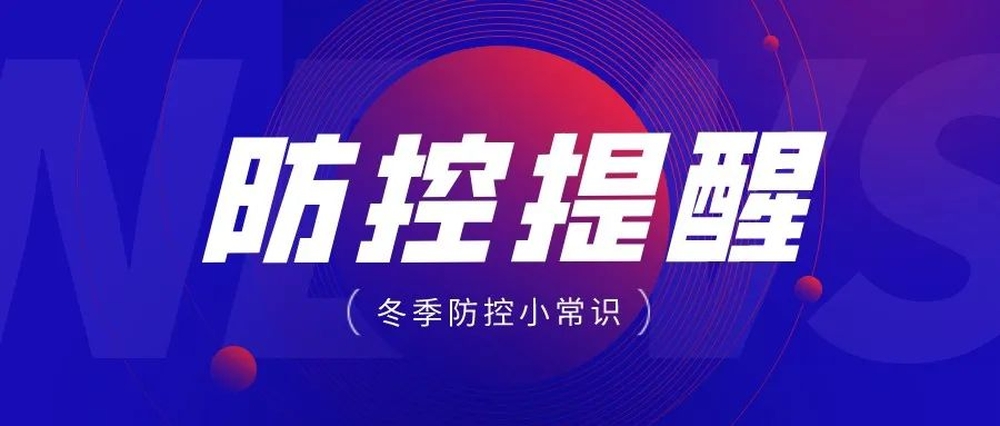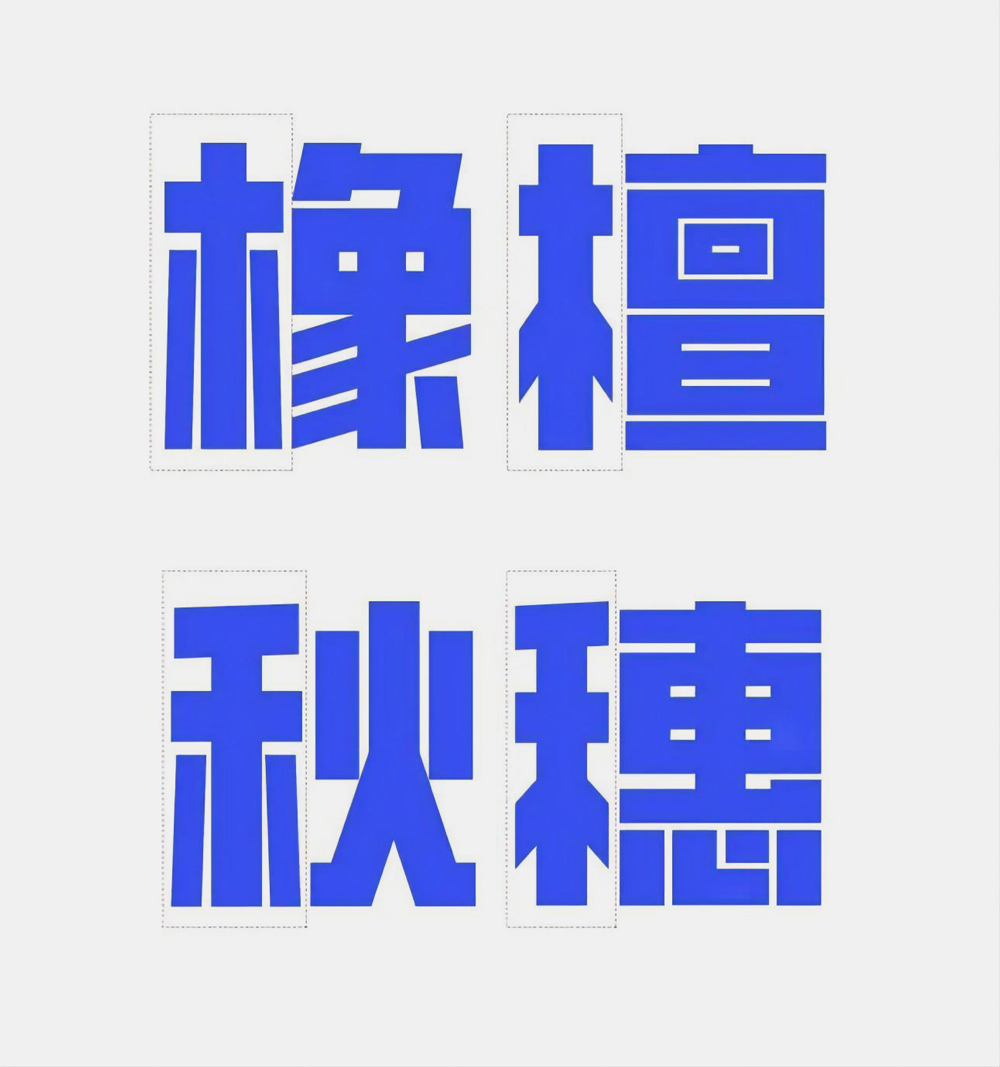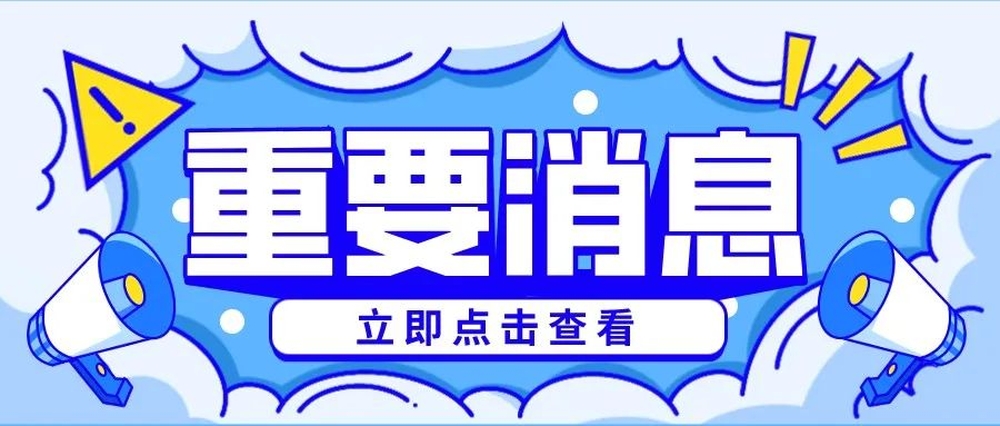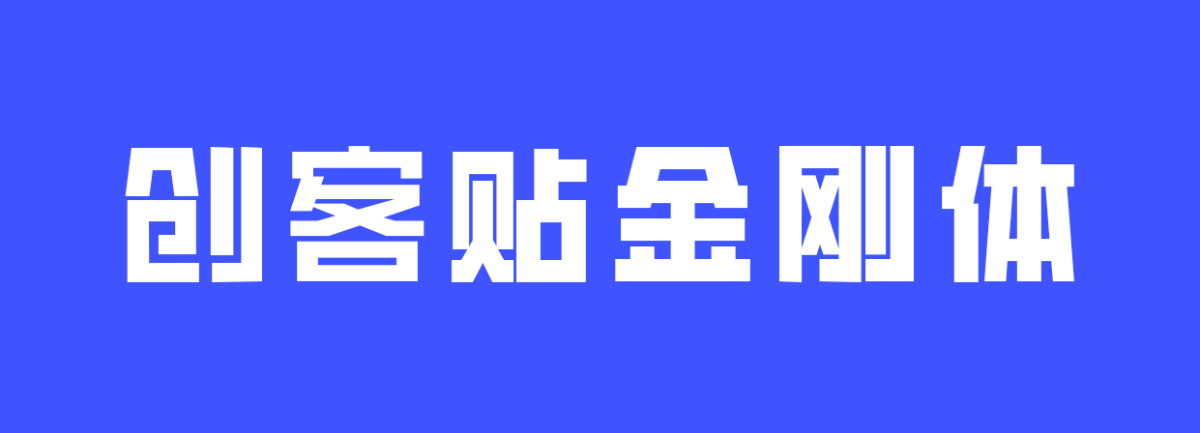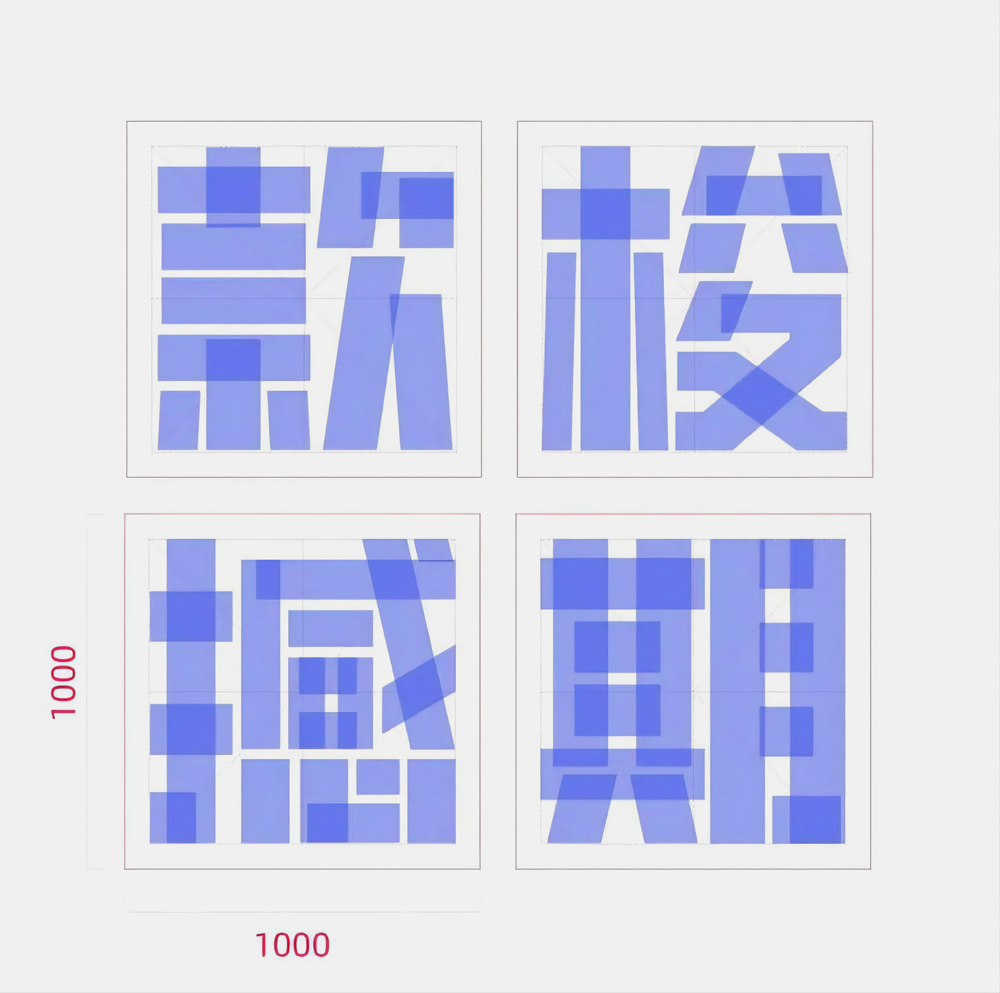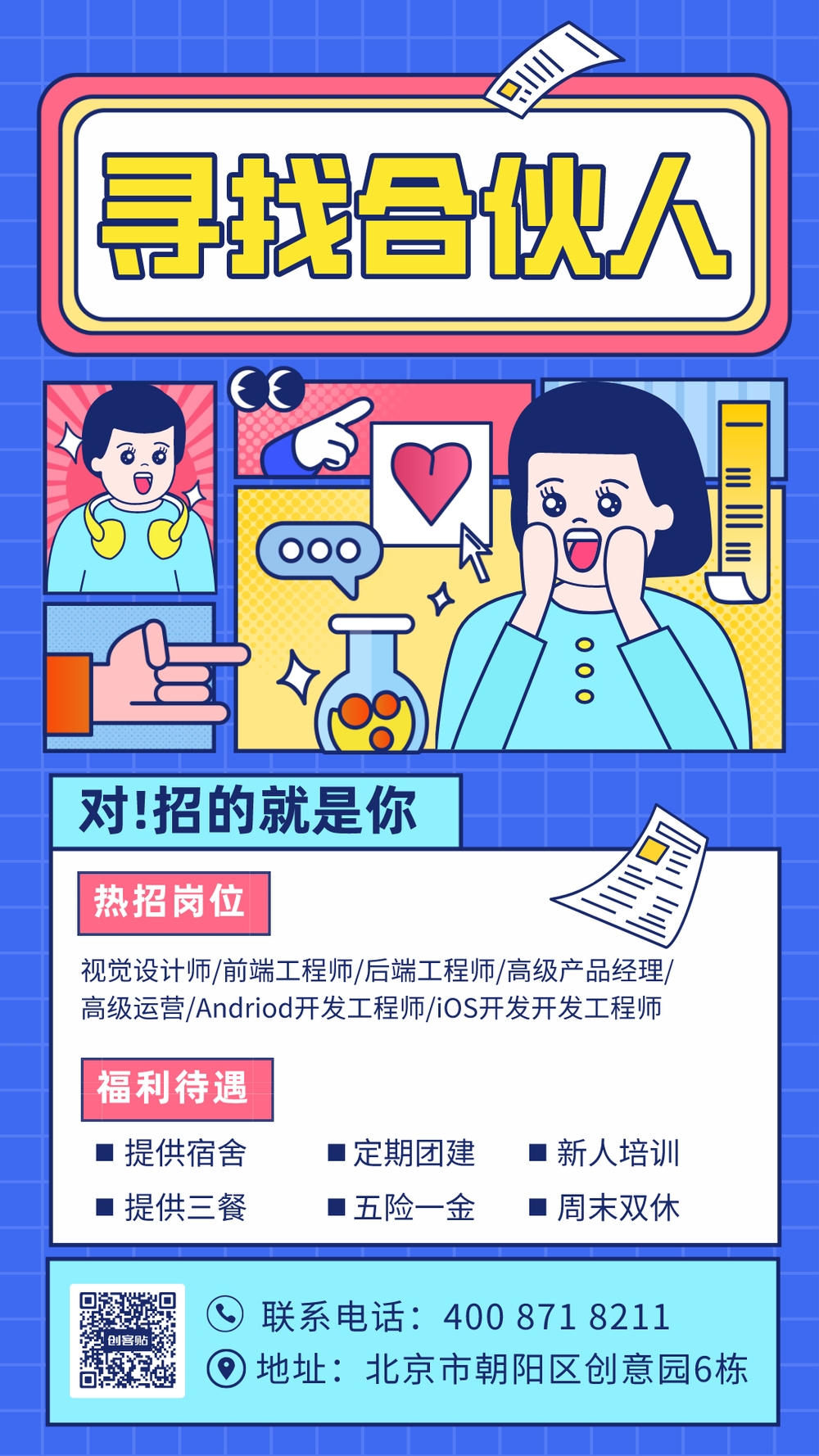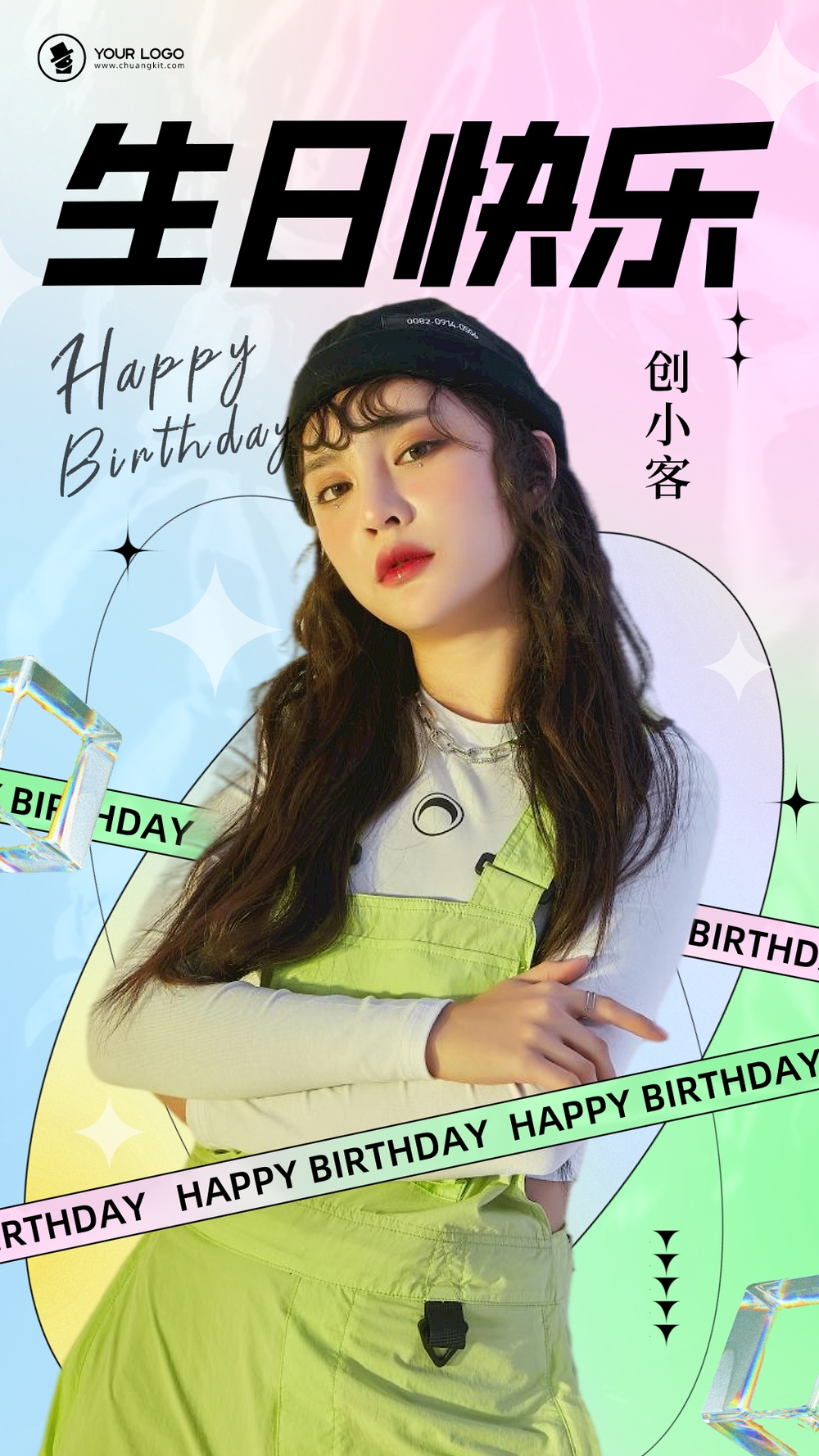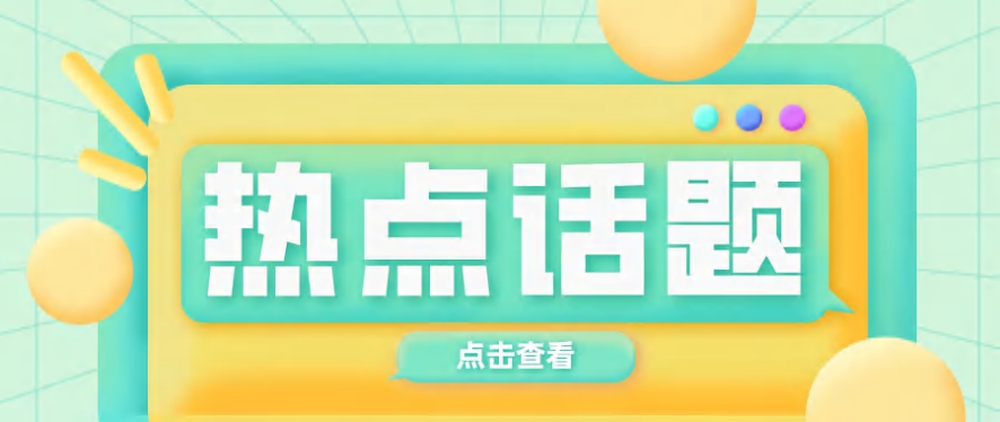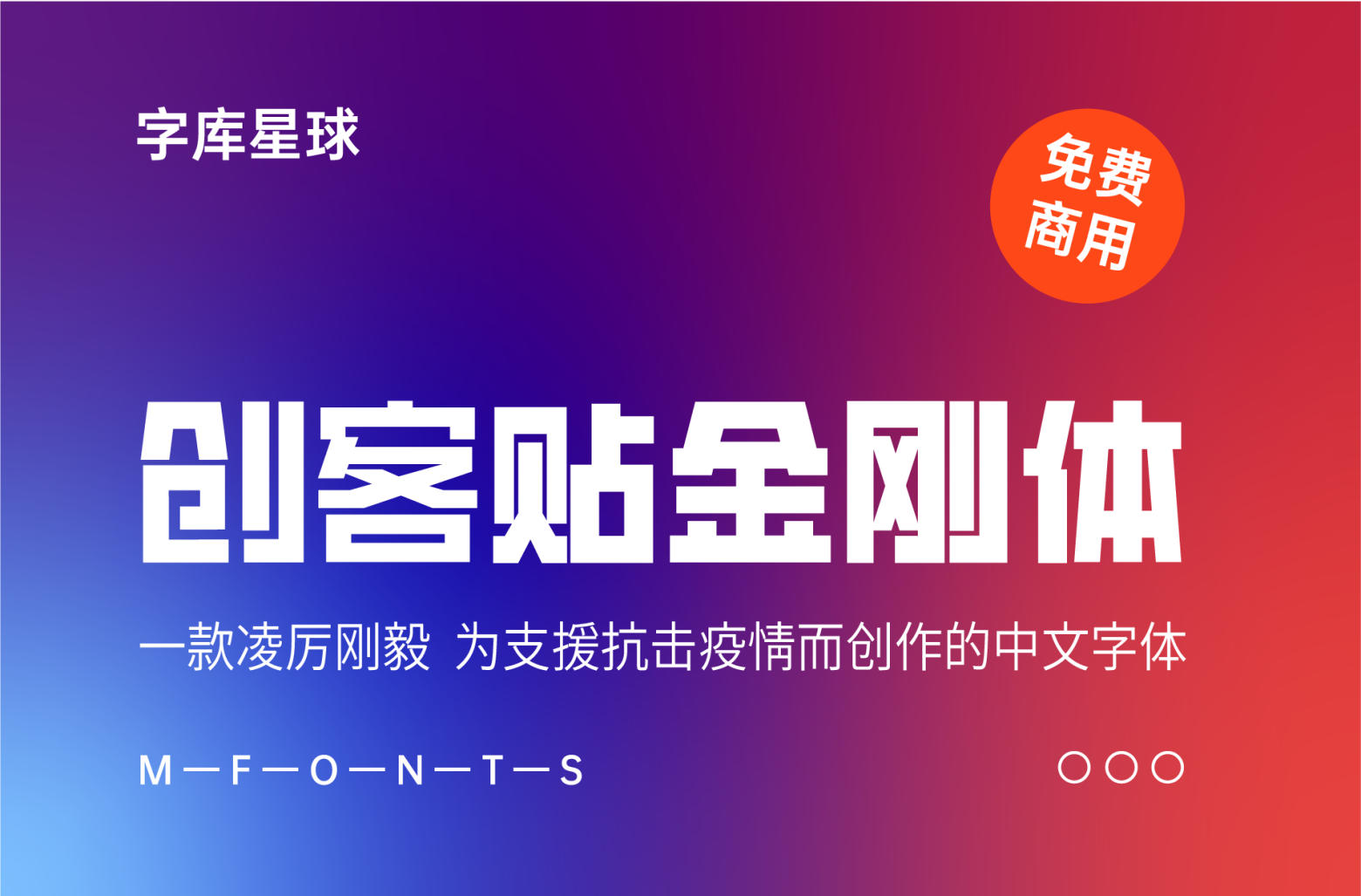
创客贴金刚体是为支援抗击疫情而创作的字体,之前只在创客贴 ckt.cn 上架了这款字体,现在庆科字体将字体安装包开放下载,并可以免费商用!创客贴金刚体的设计理念是将一切繁琐的笔画融合简化,让字体更加简约有力量,而又不影响字体的识别性,适用于商业海报、电商 banner、包装、品牌宣传。
创客贴金刚体基于中华人民共和国 GB2312-80 字符集标准,包含大陆简体汉字 6763 个、繁体中文 16 个、英文大小写 52 个,阿拉伯数字 10 个,以及 682 个符号,满足日常用字需求。字型比例1:1,笔画粗度为 150pt,非常适合用于画面标题:
省略了竖勾的勾,更有利于视觉传播:
以下是创客贴金刚体部首的多种处理方式: